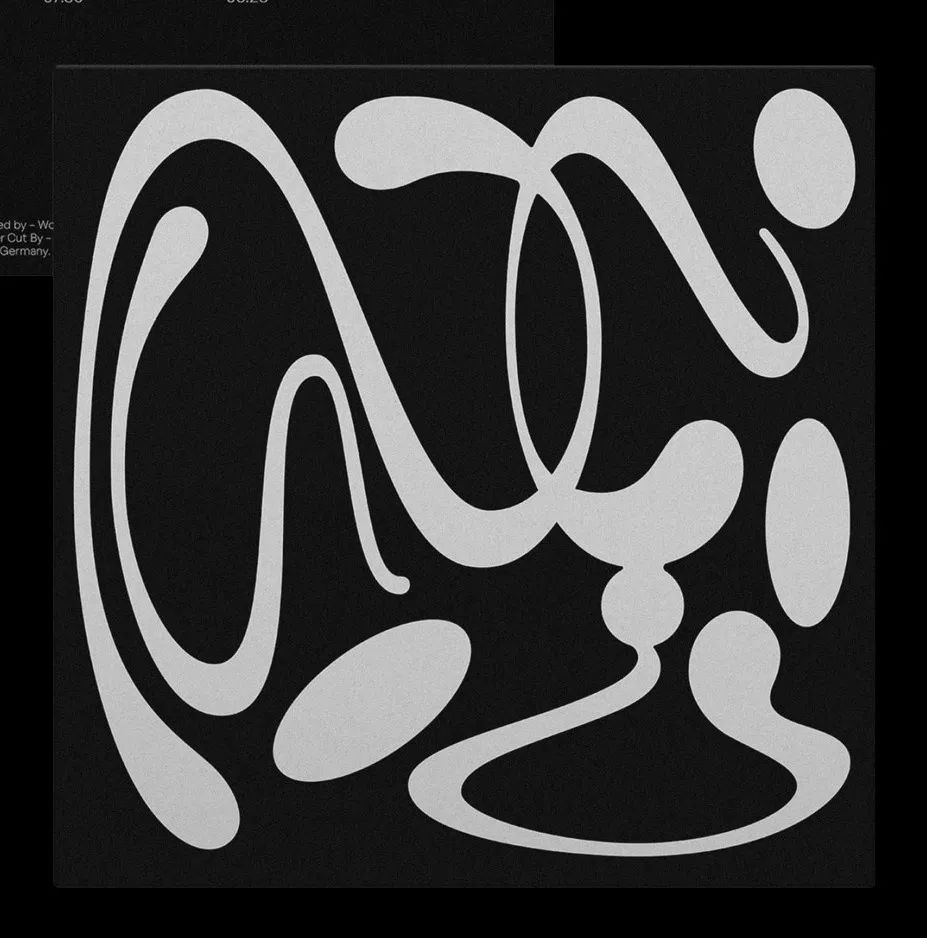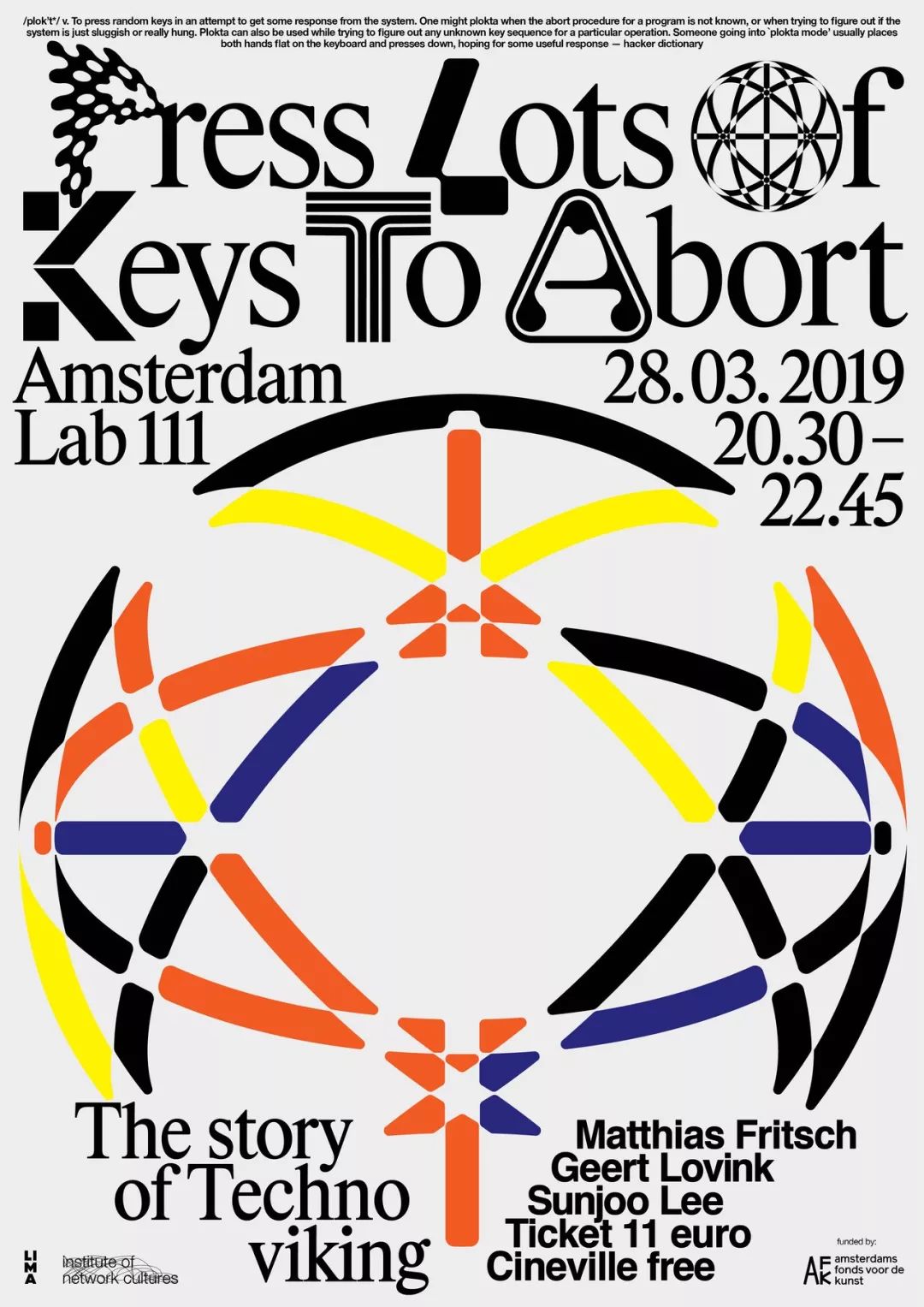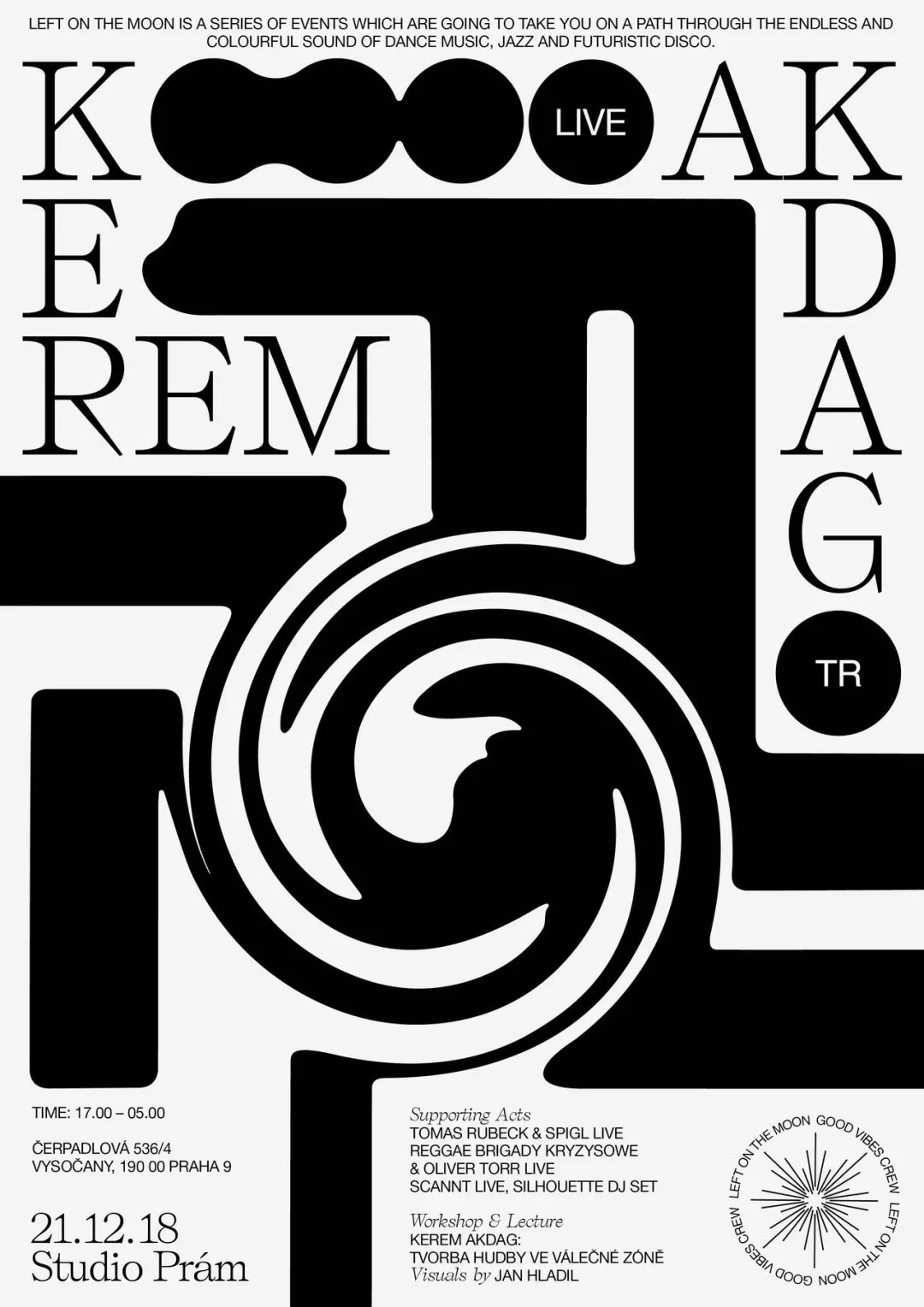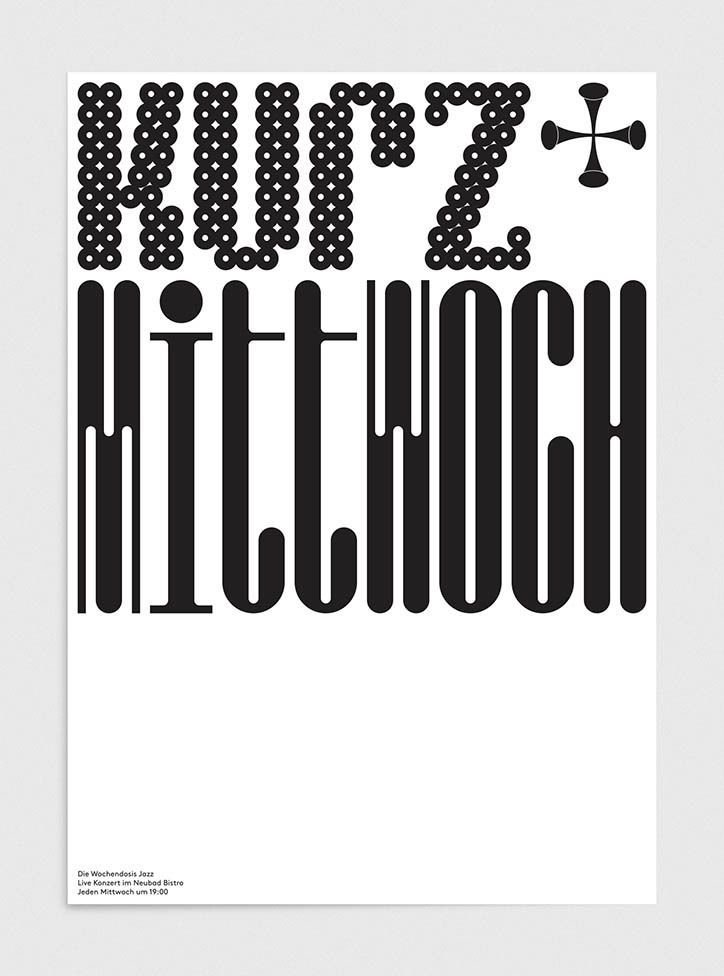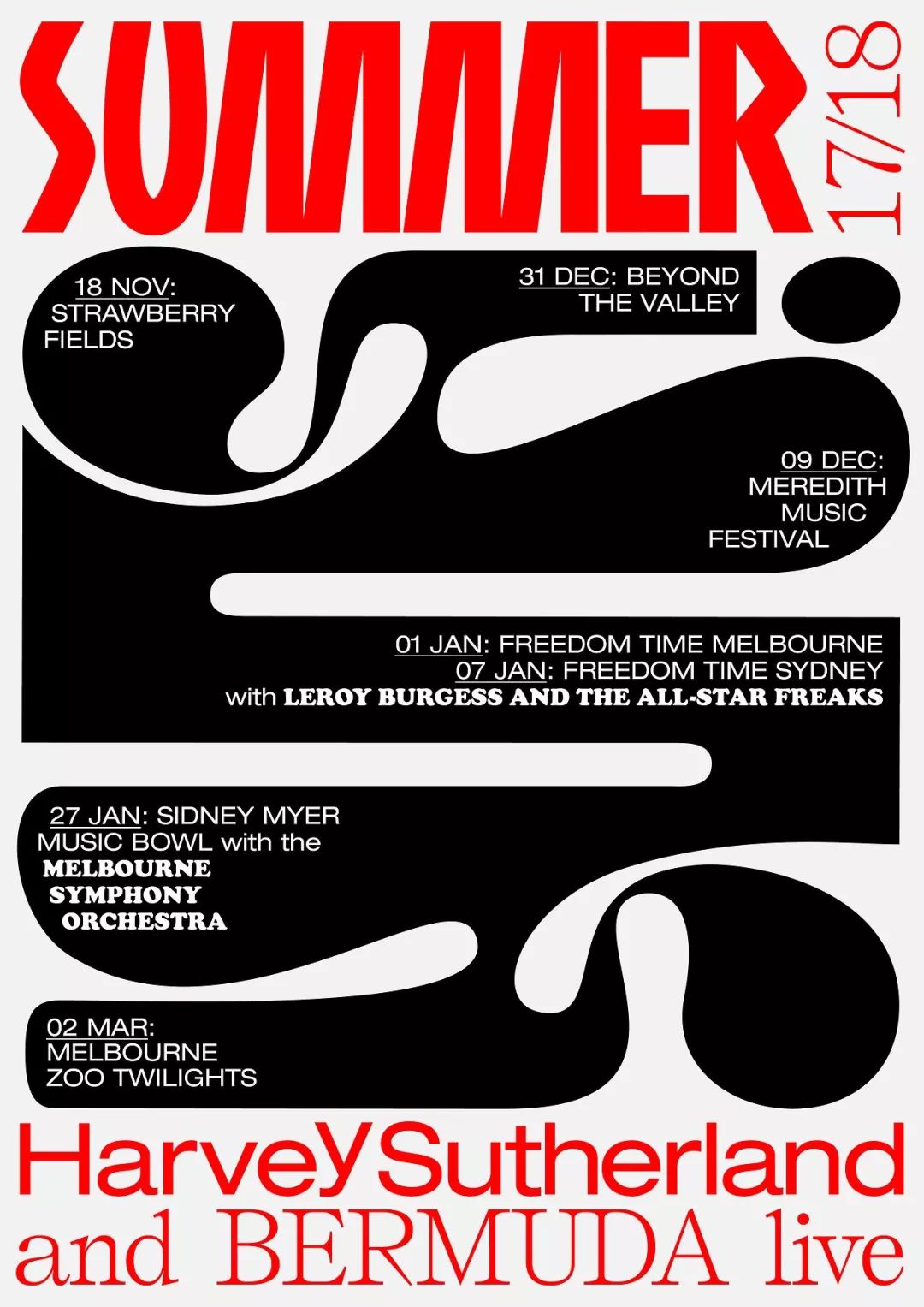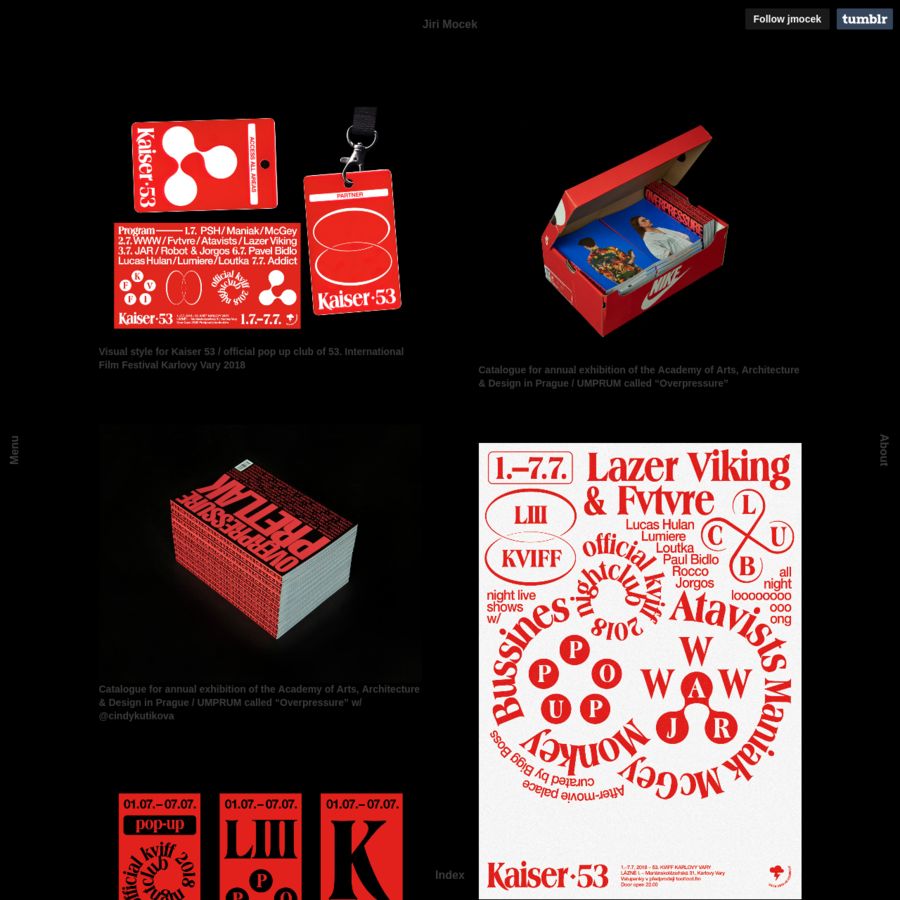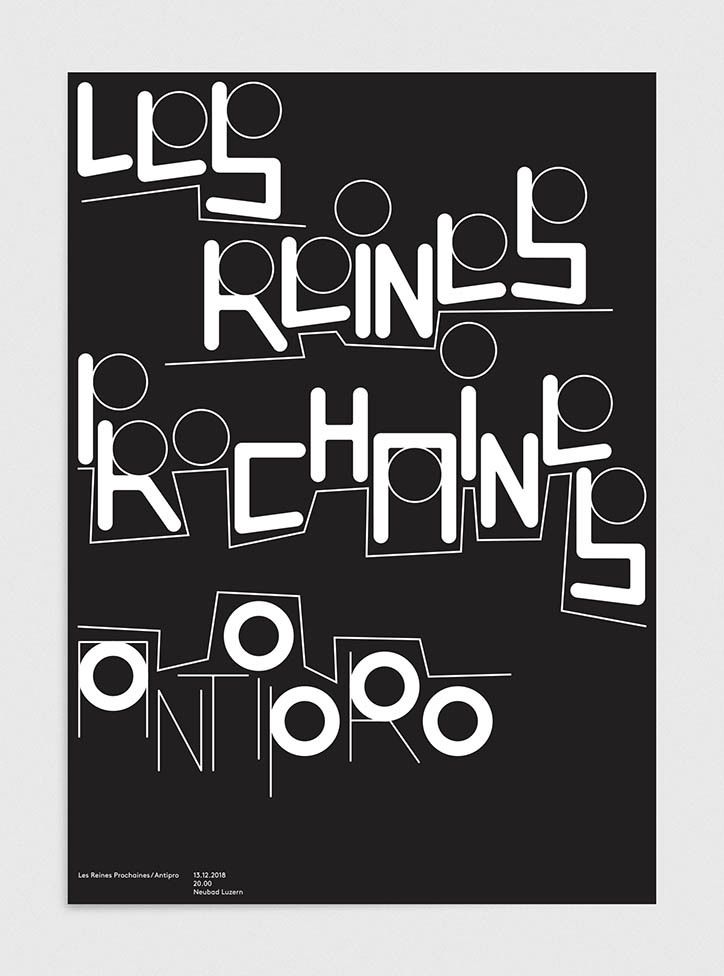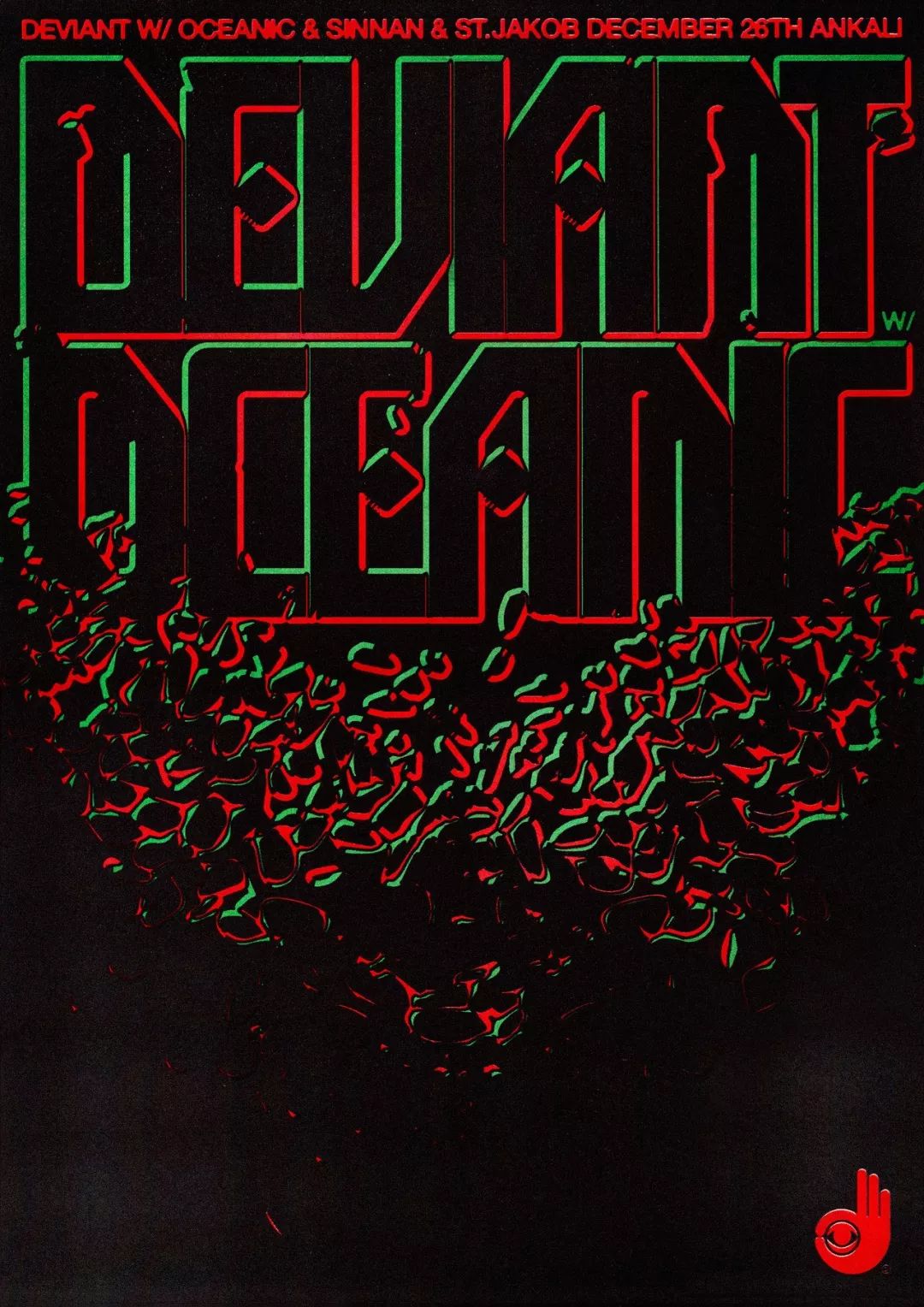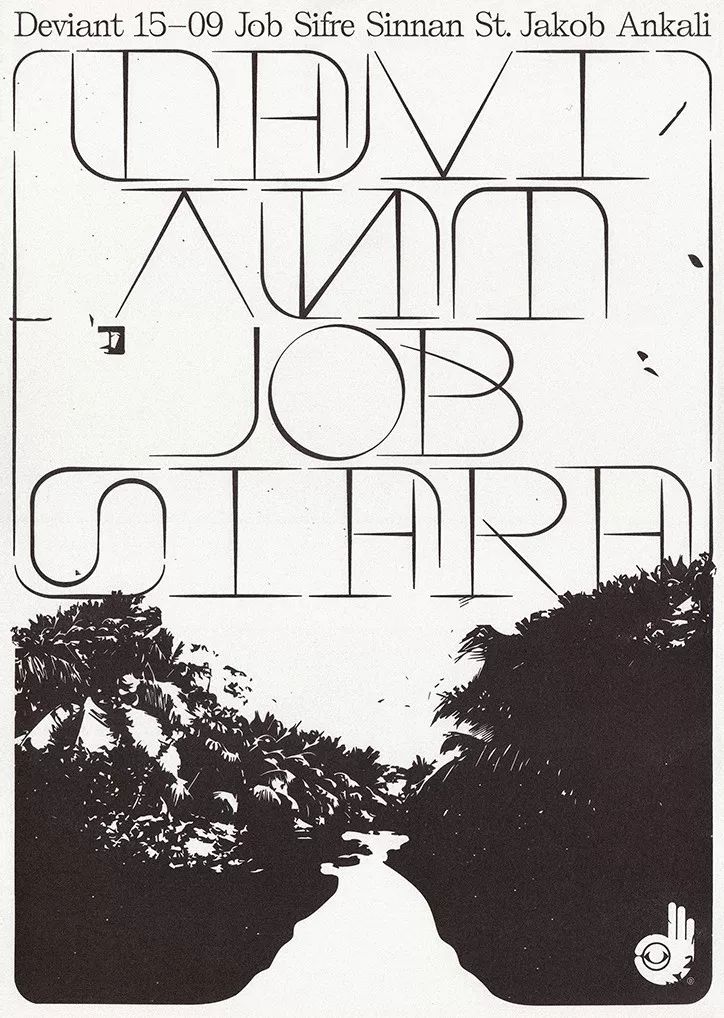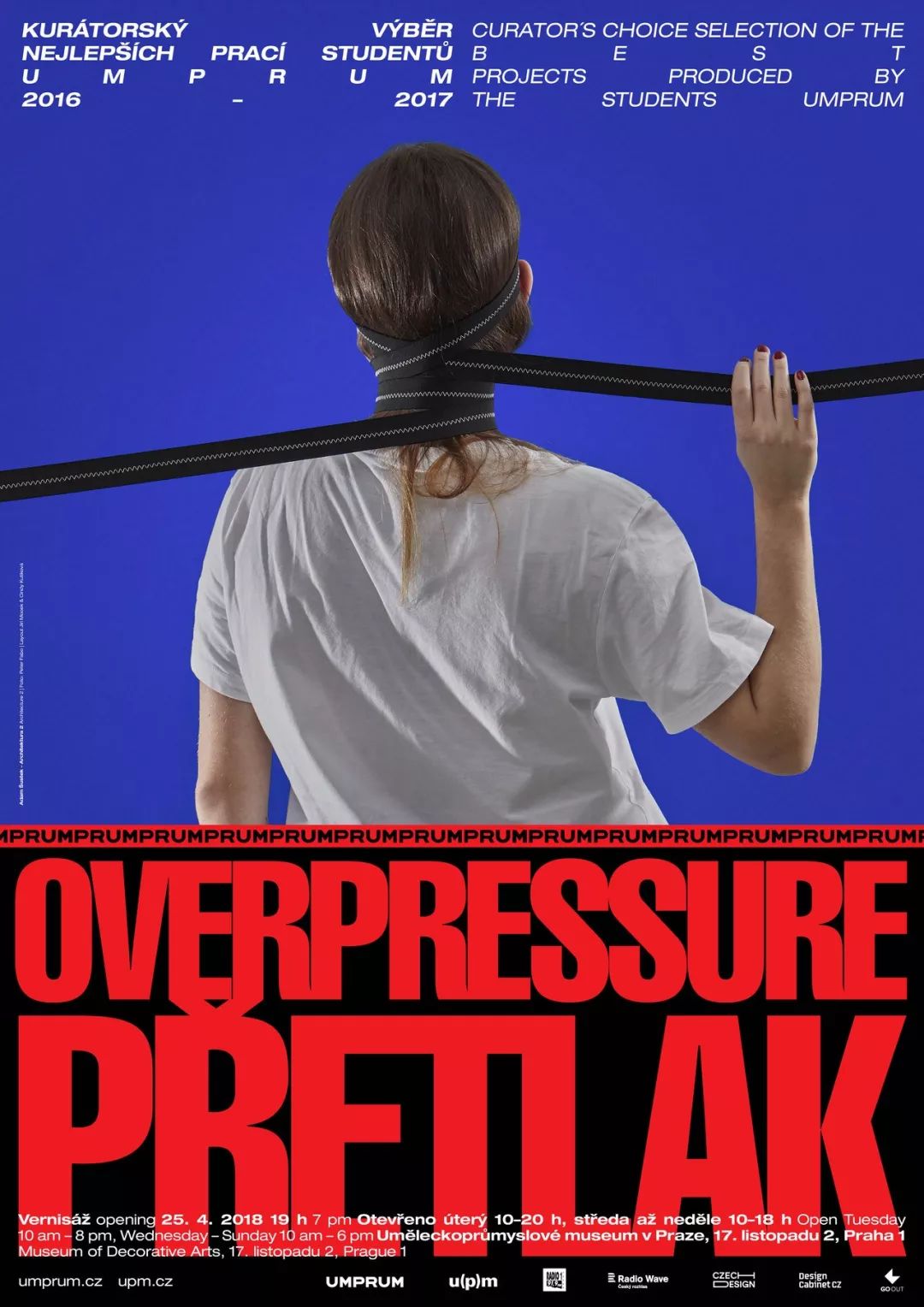
怎么将海报的字体发挥到极致!分享三位年轻设计师的方法
每位设计师对海报中的字体所起到的作用
都有不同的理解
有人认为它是承载信息的完美工具
有人认为它能直接向观者传递情绪
……
今天
我们将分享来自欧洲的三位年轻设计师
看看他们是如何结合现代技术
将字体在海报中的作用发挥到极致
NO.1
充满创意 极具表现力
首先,让我们把目光放到捷克的布拉格。
在这里,UMPRUM这样的学校自1885年就不断培养、输出着一届又一届的优秀平面设计师。悠久的历史却并没有让他们的平面设计趋于守旧,实验字体、大胆用色和新颖的3D渲染技术在这座城市的设计行业里流行。
其中就包括Jiri Mocek这样的年轻拥护者。
Jiri Mocek刚从UMPRUM毕业不久,现在是一名自由设计师,主要和音乐家、唱片公司一起合作项目。虽然初出茅庐,但年纪轻轻的Jiri却已经创建了不少令人惊艳的设计作品。而这些年来,他也如一颗迫切汲取养分的小苗,不断提升着自己的设计能力。
这里有一些他最近在社交媒体上发布的一些作品。尽管略有青涩,但不难看出Jiri对自己的作品信心十足,一种结合了各种肌理的独特字体设计风格逐渐形成。令人欣喜。
字体排版,通常都是为某个项目特别制作的独一无二的一份,这也牢牢刻在了年轻的Jiri心中。
“我想我会一直坚持钻研字体设计、文字排版,探究字体在项目中的运用。”Jiri这样描述自己目前的打算。同时,Jiri还说到,“‘字体’不仅仅是排版的一个工具而已。它更是一种可以直接传输信息、表达情绪的视觉语言。”
这一点,在Jiri有关音乐的设计中体现得尤为明显。要说到这种想法的渊源,还得追溯到 Jiri 收集唱片的这个爱好,也因为这个爱好,他逐渐走上平面设计的道路。(相关点击:设计的声音)
一路走来,Jiri为Rhythm Section这样的专业唱片公司打过工,也为家乡的大小活动设计过扑满大街小巷的宣传海报。
比如,“Deviant“——一场由布拉格本地俱乐部Ankali举办的夜晚活动,就邀请了Jiri做了海报设计。
“我们为每一场演出都制作了不同的海报。并且通过使用同样的构图、相似的风格来营造它们之间的统一性,在这基础上再添加一些定制字体,或者小插画。”
这系列的色彩均采用了Risographing打印机中有的颜色。
如果说,“Deviant“的系列设计是专注于制作过程的海报设计,那么另一个Jiri为某快闪项目设计的海报就完全是基于现场环境启发所作。
这次的快闪作为电影节的一部分,在一座文艺复兴时期的建筑里进行。
“那次的设计太让我喜欢了。整个设计都与这座充满历史感的建筑紧紧相连,运用那个时代的历史元素和历史字体也就顺理成章,毫不突兀。”
随着设计经验的不断增多,身为自由设计师的Jiri也接触了许多自由度较大的设计项目。相信未来,这位年轻的设计师也将带给我们更多优秀的海报设计。
NO.2
精心设计 精确排版
- Gianluca Alla -
“我不想局限于只做海报的平面设计师,也不想做那种只做‘动态字体’的字体设计师。”
来自意大利的Gianluca Alla不怕口出狂言,称已经厌倦了满街乱铺的平面设计。
精心设计,精确排版。
“字体设计对我来说就是视觉交流的A、B、C——强大、富有表现力,同时能给予很好的对比度。”在Gianluca理解看来,可能只是一点小小角度的改变,就能让一个正式字体转变为一个随性的字体设计。这是字体的符号语言学。
单单看设计师对字体的选择,就已经传递给了观者太多信息。
Gianluca通过他的设计证明了这点。
在一个为纽巴德小酒馆卢塞恩(Neubad Bistro Lucerne)音乐会进行的海报设计中,海报的字体是根据乐队Horizon Liquide演奏的音乐类型特别设计的。
字体设计通过之字形摇摆的线条,打破了衬线字体原本呈现的纤细雅致,很好地传递出该演奏乐队“古典、电子”的音色感。
而另一个为爵士乐队Les Reines Prochaines设计的海报,上面的字体就仿佛正随着爵士乐的节奏轻松摇摆一般灵动。
在展示关于意大利人的一些日常数据的出版物《90 Numeri Statistici》中,Gianluca利用字体设计让原本枯燥冗长的统计数据变得生动有趣。每一条不同的数据条目都被加粗显示,并且以不同的形式呈现,增加了一份华丽感。甚至这套数字还在统计节期间,被意大利特雷维索地区用作了搜寻系统的字体。这套字体的实用性可见一斑。
最后提到的,是Gianluca为动画字体项目《Letterzip》设计的一系列实验字体。展示了“平面设计如何和字体一起构建直率又抓人眼球的设计。”
Gianluca选择将简短的文字回答做成一个个强有力的动图,用动态和古怪又可爱的设计来探测文本可读性的边界。
说到动图,还记得去年圣诞节期间,Gianluca在动图平台Giphy上发布的“圣诞快乐”动图在网上疯传,仅两天时间就收获了近4000万的阅读量,获得了当时Giphy的首推。
不谈别的,仅仅是这些数据就足以证明这个设计在某个方面获得了极大的成功。
当代设计遇见古典字体
- Mateo Broillet -
我们的最后一位主人公是现居住在阿姆斯特丹的自由字体设计师Mateo Broillet。
最近,Mateo开发了一套为音乐剧节创造的字体Anzaze。
“这套字体可以直接塑造海报的结构,可塑性强。足以同时容纳两种开放式字体。除此之外,因为受中世纪版画的影响,它的拉丁字母血统在拉长的衬线和圆润的转角中得以显现。”
Mateo还补充说,“我希望Anzaze这套字体可以‘开’得更大一点,更通俗一点。它将是一套既充满历史感,又能与时俱进的字体设计。”
再前一年的音乐剧节海报设计,Mateo根据庞贝涂鸦和一种不规则图拉真皇帝字体而设计出了一套名为“Nero”的字体。
“尖锐,而又带有一种难以遮盖的傲慢。”这套强劲的字体,字母“R”的尖锐呈现更是透着一股浓浓的哥特意味,这也使得Nero字体整体给人一种诡异、精明的渗人感觉。
同样,Mateo为哈佛大学设计研究生院设计的一套视觉识别“Ward”也采用了经典字体的改编。
Mateo称说他选择这样的呈现是因为他希望Ward看起来足够“经典”,这样才能匹配哈佛的知名度及历史。
不过虽然说采用了较为古典的字体设计,Mateo仍然想让这套视觉形象成为一种强有力的设计交流字体。于是,经过努力,Ward有了现在这副模样,不仅符合传统审美,又含有诸如3D、雕塑插画这样的元素。
这个夏天过后,Mateo就要从荷兰桑德伯格学院(Sandberg Instituut)完成他的美术和设计硕士学位。
“在桑德伯格学院的学习让我更多维地了解了字体设计,接触、尝试了一些在历史和政治背景下的字体设计。”
也是这段时间,Mateo逐渐开发了一种可以将自身兴趣融入字体设计的方式。“我很享受通过字体设计排版来构建一个设计项目。我也很喜欢从字体中折射设计过程这个想法。”
如今,尚未毕业的Mateo,满怀信心,期待在设计行业中大展身手。